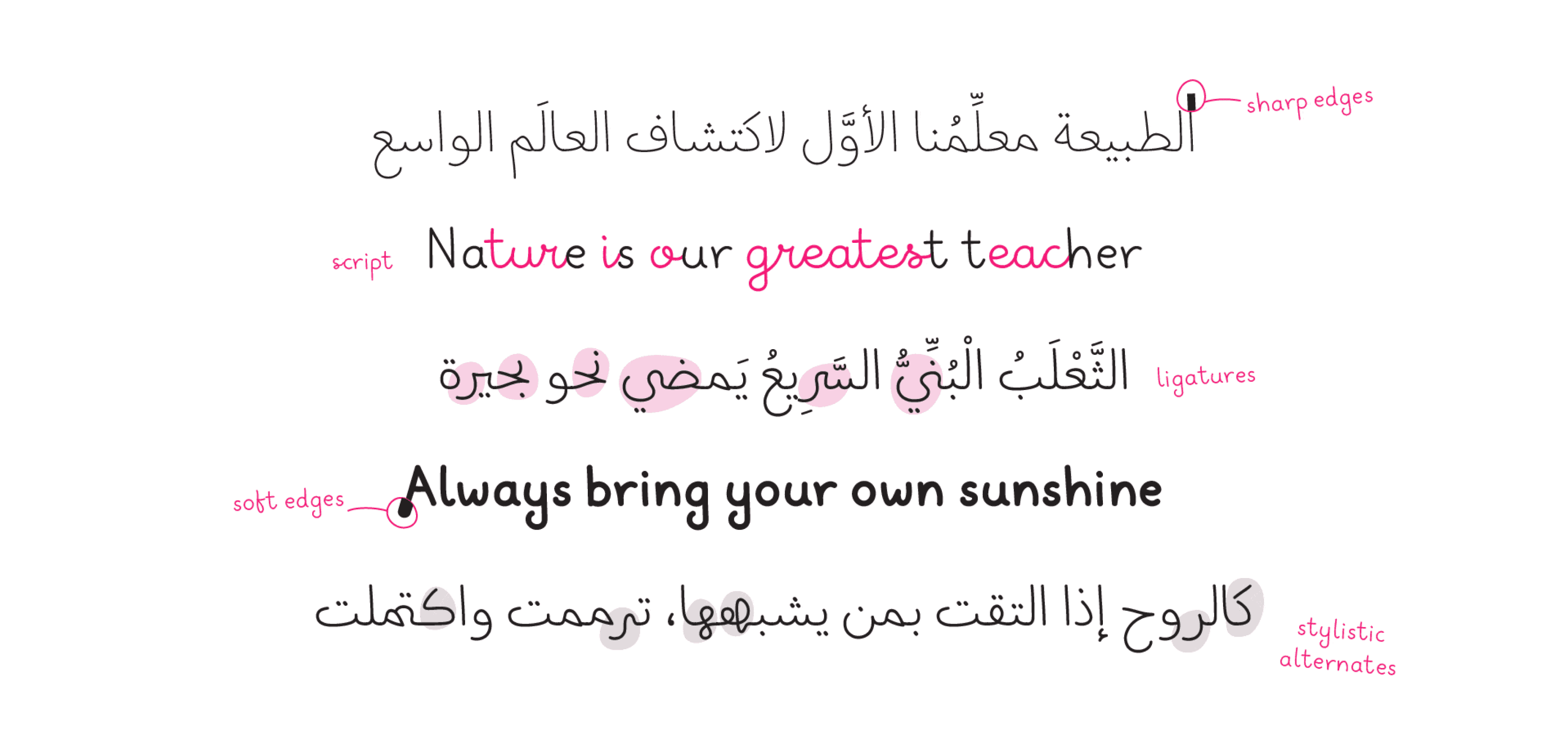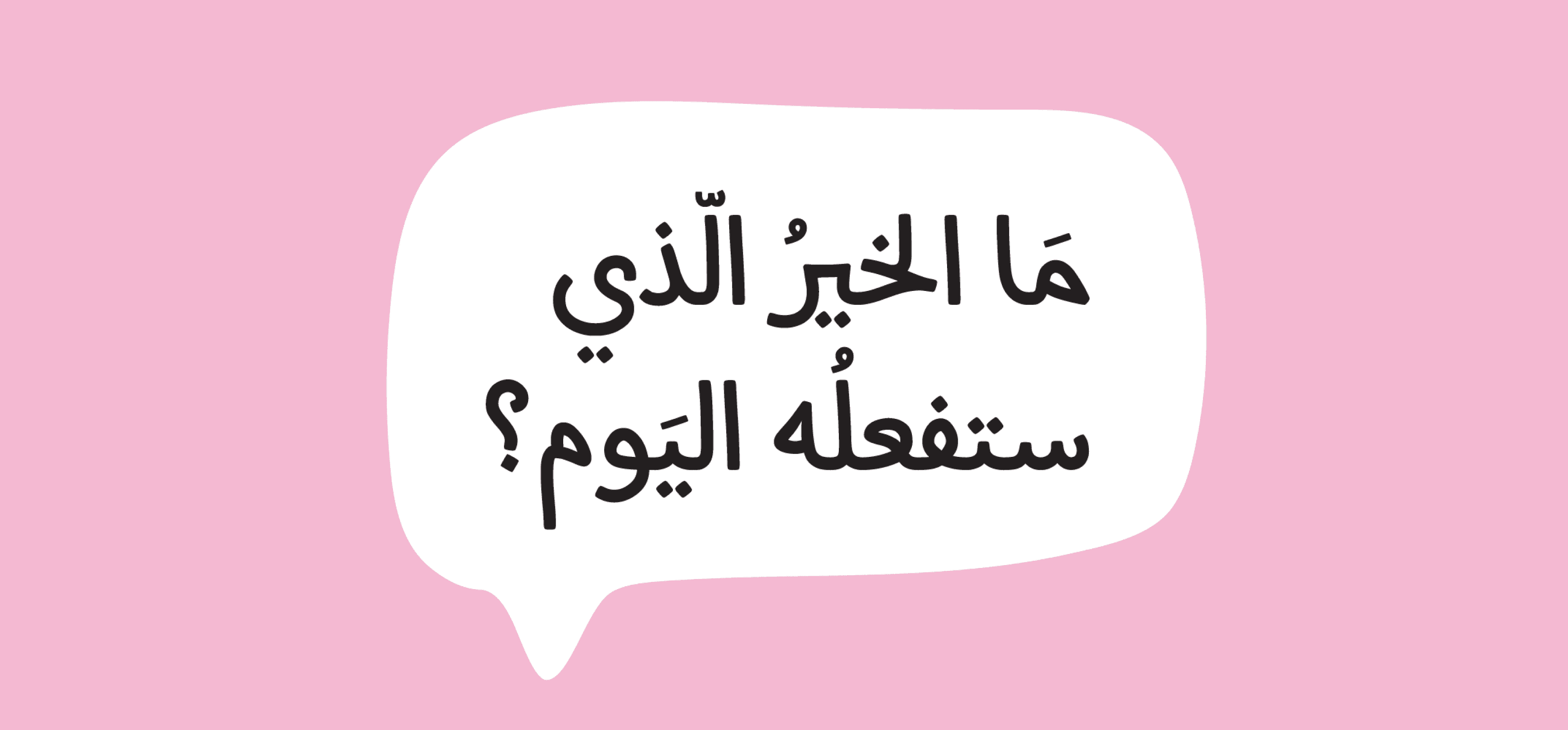
صممت خط ملهم لأول مرة في عام ٢٠١٦ كمشروع شخصي لتوثيق خط کتابتي اليومية. كان خط ملهم ٢٠١٦ خطًّا ثابتًا بوزنين (عادي أو سميك) فقط ولم يدعم سوى اللغة العربية. نظرًا لأنها كانت تجربتي الأولى في تصميم الخطوط فقد كانت في النسخة الأولى من الخط العديد من المشكلات المتعلقة بتصميم أشكال الحروف والجماليات، ورسم المنحنيات، ونسب الحروف إلى بعضها، وبرمجة الخط، واستخدام ميزات أوبن تايب المناسبة.لذلك في عام ٢٠١٩ شرعتُ في إعادة تصميم خط يدي مجدَّدًا من أجل إنتاج خط أكثر أناقة أولًا، ومرونةً ثانيًا من حيث تعدد اللغات وتنوع الاستخدامات. للارتقاء بالجانب الجمالي أولًا، قمت برسم أشكال الحروف العربية مرةً أخرى مركزةً بشكل أساسي على تناسب وانسجام مجموعة الحروف. هذا بجانب إضافة أكثر من ٢٠٠ محرفٍ مقرونٍ، وأشكال مختلفة للحرف الواحد للإبقاء على الإيقاع الطبيعي لخط يدي.أما لجعل الخط أوسع استعمالًا فقد قمت بإضافة مئات المحارف حتى تعدى خط ملهم المتغير الجديد اللغة العربية إلى شبيهاتها مظهرًا من اللغات كالفارسية والأردية، فضلاً عن الأحرف اللاتينية الأساسية والممتدة. بجانب ذلك فقد عملت على توسيع دائرة استخدام الخط حتى في نطاق اللغة الواحدة بإضافة خاصية التغير التي يأتي منها اسم "خط ملهم المتغير". بدلاً من تخيير المستخدم بين عدد محدود من خيارات وزن أو هيئة الخط (عادي أو سميك، ناعم أو حاد) تمنح خاصية التغيّر المستخدم الحرية في تحديد سمك الخط وحِدّته وذلك في محورين: محور الوزن، ومحور النعومة. يتدرج محور الوزن من رفيع إلى سميك، بينما يغيّر محور النعومة حدود المحارف من طرف دائري إلى طرف حاد.على الرغم من أنني أعتبر "خط ملهم المتغير" خطًّا جديدًا ومختلفًا من نواحيَ عديدة، قررت الاحتفاظ باسم "ملهم" للخط الجديد لاتفاقه مع سابقه في فكرة إنشاء خط رقمي من كتاباتي اليدوية اليومية، وأنني أتمنى أن يجد مستخدمو الخط الإلهام فيه.